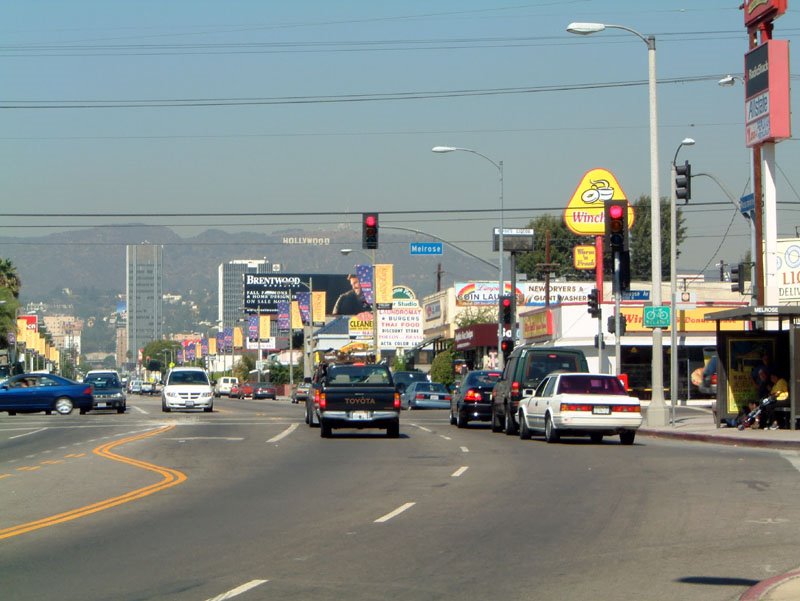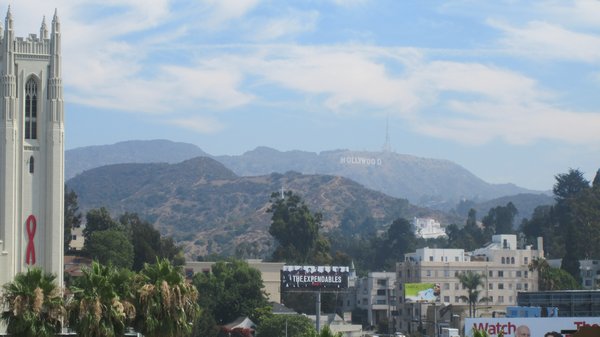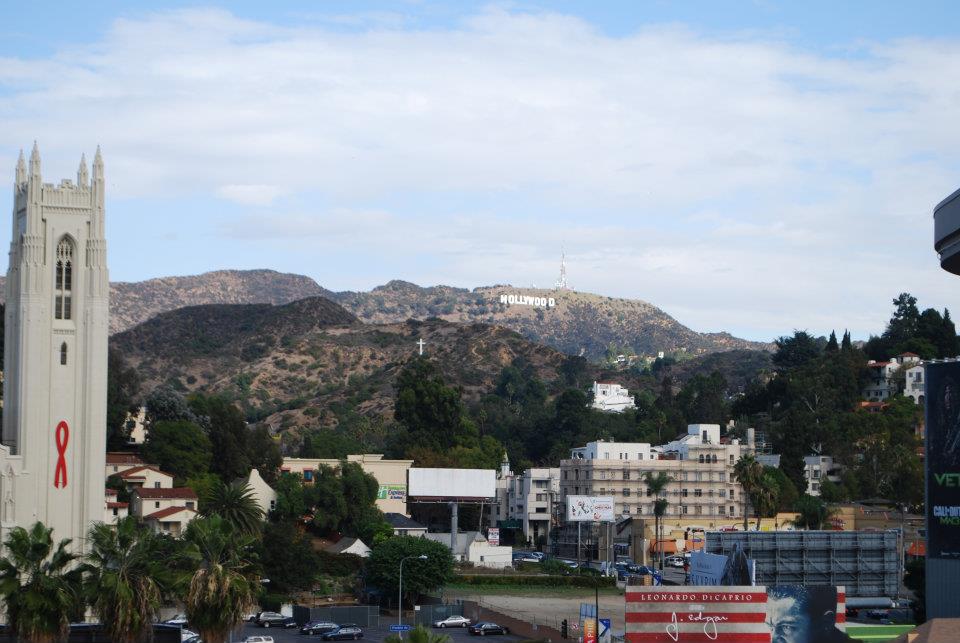
Schriftgröße (große Entfernung)
Gibt es eine Tabelle, die eine Lesbarkeit nach Entfernung angibt?
Es geht um Entfernungen in der Landschaft, ca. 3 - 4 km
Text wird auf einen Berg gemalt.
Spannend! Kannst du mehr zu dem Projekt verraten?
Bräuchte man in 🇩‍🇪🇦‍🇹🇨‍🇭 (oder wo auch immer das stattfinden soll) für so etwas eigentlich eine Genehmigung?
Ansonsten würde ich noch zu bedenken geben, dass bei solch großen Entfernungen eine Größe nach sizecalc.com bzw. einer der verlinkten Formeln mglw. nicht ausreicht, da 3 km Luft zwischen Betrachter und Berg je nach Wetter ganz schön flimmern können.
Bei solchen Aufgabenstellungen rechne ich bevorzugt mit dem Strahlensatz und werfe da die mir bekannten Randbedingungen ein. In dem Fall würde ich mir in einem Meter Abstand so was wie ein Modell denken und/oder skizzieren, die Höhe der Buchstaben abmessen und dann müsste man nach Strahlensatz nur noch die Größe des Modells mal 3000m/1m = 3000 nehmen. Aber Achtung! Das wird ziemlich groß werden. Aus 1 mm im Modell werden da schnell 3m ... Aus 4 mm Buchstabenhöhe dann 12 m ... Bist Du sicher, dass Du das auch wirklich umsetzen kannst?
Das Flimmern sollte weniger das Problem sein. Dieses tritt am stärksten wenige cm über dem Boden auf, so dieser sich stark aufheizt. Der Boden kann eine Alspahltdecke oder aber auch ein Flachdach sein. Das tut er erst mal sehr selten, nur im Sommer bei extremen und dabei windstillen Strahlungstagen und dann sind die paar mm Verschmieren auf dem sehr viel größeren Ziel total irrelevant. Die 3 km flimmern so gesehen erst mal gar nicht, nur wenige cm oder Meter können es und dann ist der Verkehrsteilnehmer mit etwas Glück darüber erhaben.
Nebel und Dunst sind wesentlich relevanter. Von Nebel spricht man bei Sichtweiten unter 1 km, von Dunst bei Sichtweiten über 1 km. Um da einen kleinen Überblick zu erhalten kann man sich Flugwetterdaten ansehen. CAVOK -> Cloud and Visibility OK bedeutet dann mindestens 10 km und ist nicht mal sooo selten. Ob dann auch noch tief(f)liegende Wolken relevant sind ist eine Frage der Topografie und des typischen Wetters in der Gegend.
ich habe gerade mal aus dem Fenster gesehen und mir die Fenster an entfernten Gebäuden als Maßstab für etwa 1 m hohe Versalien vorgestellt. Das wird aus einem km Abstand zwar lesbar, aber nicht sehr auffällig. Auf 3 km umgerechnet wären das bereits 3 m hohe Buchstaben und diese wären trotzdem sehr unauffällig, also leicht zu übersehen. Es geht also nicht nur um die Lesbarkeit sondern auch um die Aufmerksamkeitssteuerung, also das Einfangen des Blicks.
Praxistipp für Großstadneurotiker: Sucht Euch eine auffällige Beschriftung an einem Gebäude aus, messt oder schätzt deren Höhe ganz grob ab und entfernt Euch dann davon. Ab wann wird die Schrift unauffällig und/oder unlesbar? Bei bekannter Position kann man das aus dem Stadtplan in Papierform oder auf einer Äpp leicht ablesen. Ganz grob würde ich da von einigen Gebäudefassaden in der sehr nahen Umgebung angeben: 1/3 bis 1/2 m hohe Buchstaben fangen ab etwa 200 oder maximal 300 m den Blick ein. Das wären dann auch schon mal fast 2 m Buchstabenhöhe pro km Abstand. Damit würde ich bei 3 km auf mindestens 5 m Buchstabenhöhe schätzen. Zur besseren Vorstellung: Das entspricht in etwa der Höhe von (nicht ganz) zwei Stockwerken in Wohngebäuden.
Praxistipp für Landeier: Schaut einfach auf ein in etwa gleich weit entferntes, mehrstöckiges Gebäude. Dann stellt Euch vor über wie viele Stockwerke die Buchstaben gehen müssten um diese eindeutig erkennen zu können. Stellt Euch dazu einfach die Buchstaben auf die Hausfassade gepinselt vor und rechnet dann mit 2,5 bis 3 m Stockwerkhöhe.
Ich habe schon ein Testwort mit 6m Schrifthöhe und das ist noch nicht klar identifizierbar. Deshalb habe ich versucht, dass ich mich mal bei Fachleuten umhöre. Das mit der Formel nach sizecalc konnte ich noch nicht verstehen - gegeben habe ich ja nur die Entfernung.
Das Projekt ist ganz leicht erklärt: Ich möchte auf meiner Gästefarm in Südafrika unseren Namen an einen Hügel schreiben, damit die Urlauber von der Autobahn, die ca. 3 - 4 km entfernt verläuft,   auf uns aufmerksam werden.
Das sieht man aber (in ein paar Jahren) dann eben auf Google Earth nicht.
Das fällt unter das Thema Nachhaltigkeit, vielen dank für den interessanten Aspekt.
Vielen Dank, der Gedanke ist schon richtig. Nur hier in der Wüste gibt es viele Umstände, die dagegen sprechen, z.B. keine Ausfahrtsschilder usw.
Außerdem, was in 3-4 km entfernt steht oder liegt, wird weniger behelligt.